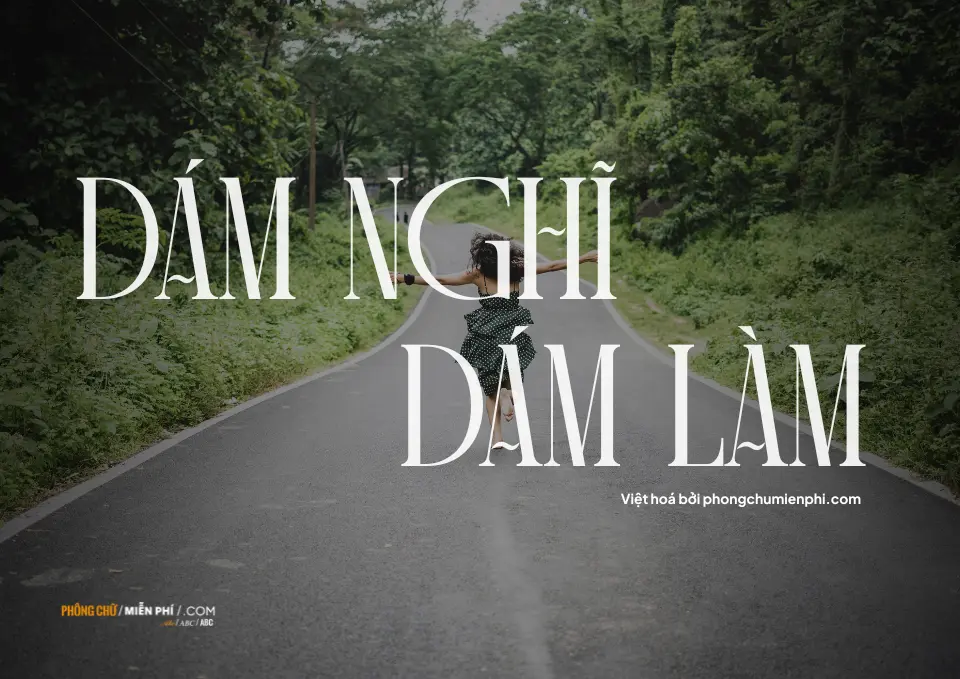
PCMP Camiro mang phong cách serif sang trọng, thanh lịch và đầy tinh tế. Đây là một font chữ có chân cao ráo, sắc nét, vừa toát lên vẻ cổ điển quý phái, vừa giữ được hơi thở hiện đại, lý tưởng để tạo dấu ấn độc đáo trong những thiết kế cần sự đẳng cấp.
Đặc điểm nổi bật
Font Việt hoá với nét có chân duyên dáng, chiều cao ấn tượng và tính thẩm mỹ cao.
Màu sắc thiết kế sang trọng, giúp gây ấn tượng mạnh ngay từ ánh nhìn đầu tiên.
Tính ứng dụng rộng rãi, đặc biệt phù hợp cho các ấn phẩm cao cấp.
Ứng dụng nổi bật
Thiết kế thiệp cướiHoàn hảo để in tên cô dâu chú rể, lời mời, menu tiệc hay bảng tên khách mời. Những đường nét thanh mảnh, cao ráo sẽ biến mỗi tấm thiệp thành một tác phẩm nghệ thuật, lãng mạn và trang trọng.
Thiệp mời & sự kiệnPhù hợp cho các buổi tiệc, lễ khai trương, hoặc sự kiện đặc biệt, giúp tấm thiệp trở nên sang trọng và cuốn hút.
Thiệp chúc mừngTạo điểm nhấn tinh tế cho thiệp sinh nhật, kỷ niệm hoặc các dịp lễ quan trọng, giúp lời chúc thêm ý nghĩa.
Ấn phẩm cao cấp khácLý tưởng cho bìa sách, tạp chí, hoặc các thiết kế mang phong cách cổ điển nhưng vẫn thời thượng
Kết luận
Với Font Việt hoá PCMP Camiro, bạn sẽ sở hữu một phông chữ mang vẻ đẹp vượt thời gian, dễ dàng thổi hồn sang trọng và cảm xúc vào mọi dự án thiết kế. Đây chắc chắn là lựa chọn hoàn hảo cho những ai yêu thích sự tinh tế và muốn tạo dấu ấn khác biệt.